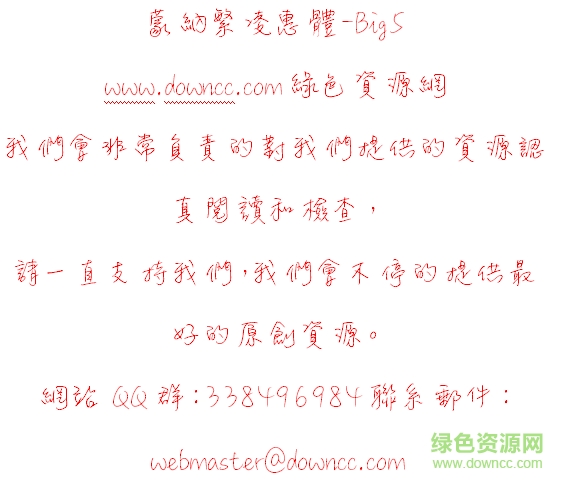
蒙納繁凌惠體是一款常見的繁體輸入的鋼筆手寫體,讓文字變得更加隨性和自由,風(fēng)格獨(dú)特深受排版設(shè)計(jì)人士的喜愛,綠色資源網(wǎng)誠(chéng)意推薦!
蒙納繁凌惠體包括蒙納凌惠f、蒙納凌惠p和蒙納凌惠big5,每一款在字形上相似,但結(jié)構(gòu)上略有區(qū)別,綠色資源網(wǎng)為大家?guī)淼氖敲杉{凌惠big5繁體,更顯活動(dòng)飄逸。
蒙納凌惠體為臺(tái)港澳地區(qū)使用的大五碼(BIG5)字體,所以在使用時(shí)不管這字體是簡(jiǎn)體還是繁體的,都必須直接輸入繁體字(如極點(diǎn)五筆輸入法就有這個(gè)功能)才能顯示所有文字,如果你輸入的是簡(jiǎn)體字,有的字就顯示為空白了。